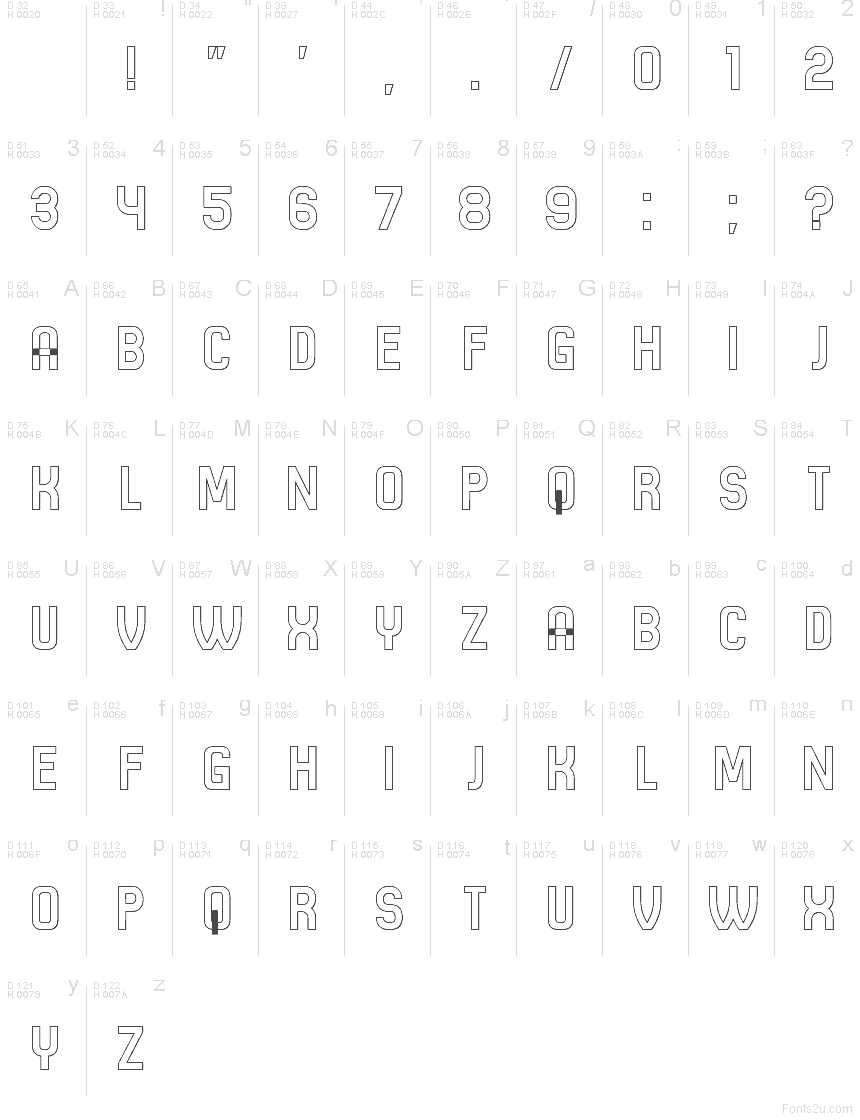
Browning 3D 由 Vladimir Nikolic 设计,是一款免费的空心无衬线字体,以高挑的大写字母和简洁的立体回声效果为特色。该字体具有建筑感和海报风格,宽大的弧线与笔直的边线确保了字母的清晰度,而双线处理则增添了一种轻盈且通透的深度感。
它非常适合用于品牌设计、包装设计、海报标题、杂志封面以及标题排版,在需要视觉张力却不想使用厚重色块的场景中表现出色。作为一款免费字体,它也十分适合用于制作字母组合或简短的文字标志,因为其开放式的 3D 处理方式即使只用几个字母也能展现出极强的存在感,足以撑起整个设计版面。
Browning 3D